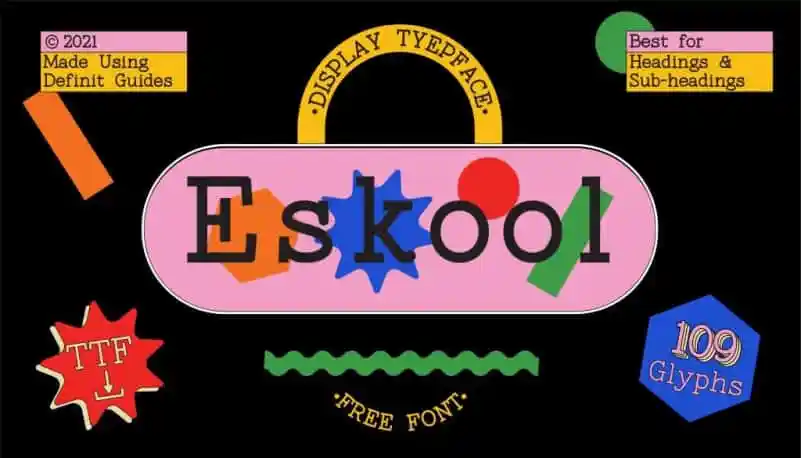
Eskool Slab Serif Font – Fonte Grátis
Eskool Slab Serif Font
A Eskool Slab Serif Font é uma opção simples e elegante para designers que buscam uma combinação harmônica entre a simplicidade das serifas retangular e os toques modernos. Ela foi criada pelo designer Saksham Verma, que conseguiu transmitir essa mistura de elementos clássicos com novidades através da forma controlada dos caracteres. Este pacote de fontes serve como uma ótima opção para aqueles que procuram uma fonte fácil de usar e versátil para seus projetos, seja em editoriais de jornal ou em logotipos modernos. Com aparência clean sem perder a personalidade mais tradicional das serifas retangulares, ela é perfeita para quem valoriza tanto o passado quanto o presente na sua identidade visual.